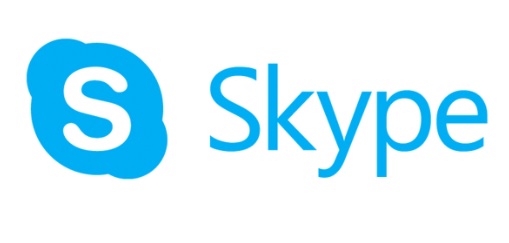
El pasado 1 de junio Microsoft anunció el cambio de imagen de Skype; la cual, se dio de manera intermitente en todas las plataformas en las que esta tiene presencia.
Es menester señalar que este cambio es un intento de Microsoft por crear un Branding consistente en todas sus marcas; Xbox, Skype, Office, Skydrive, etc…
Razón por la cual, este nuevo diseño de Skype agrega algunos elementos a la marca como lo es la tipografía corporativo de Microsoft; y la cual, ya se encuentra presente en algunas de las marcas de la empresa; y la cual, es la segunda tipografía contenida en este nuevo logotipo.
Esta situación es uno de los puntos con más críticas; ya que dos tipografías en un mismo diseño es casí un pecado para algunos diseñadores; los cuales, toman como un error de diseño la inserción de dos tipografías distintas en un mismo logo.
Skype cambia de imagen con nuevo logo y tipografía